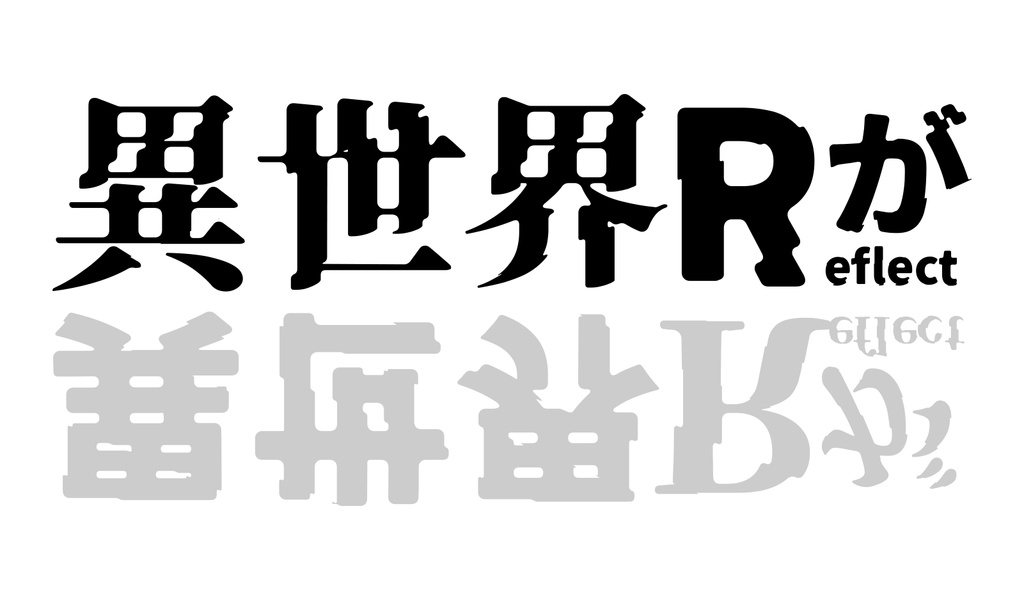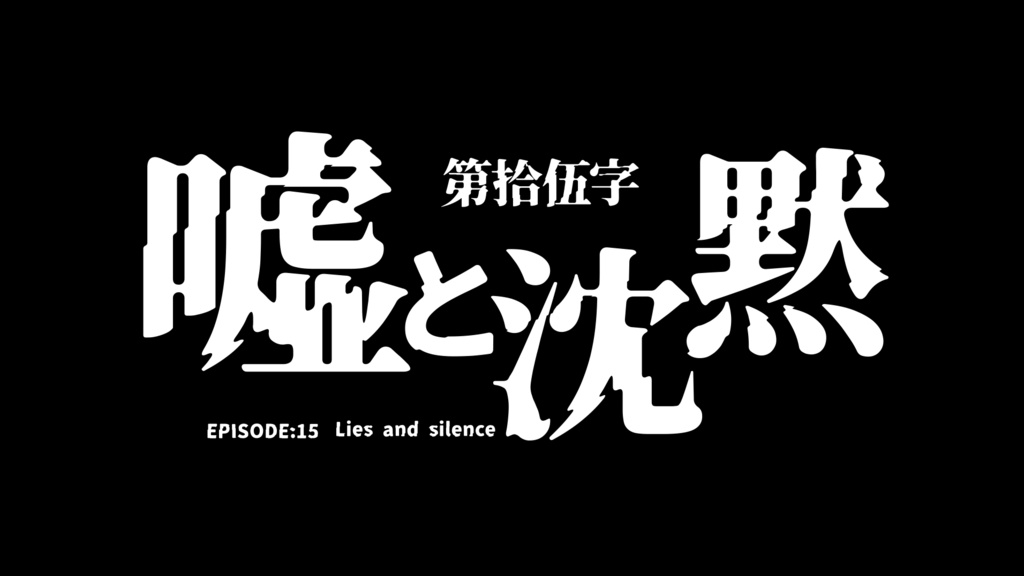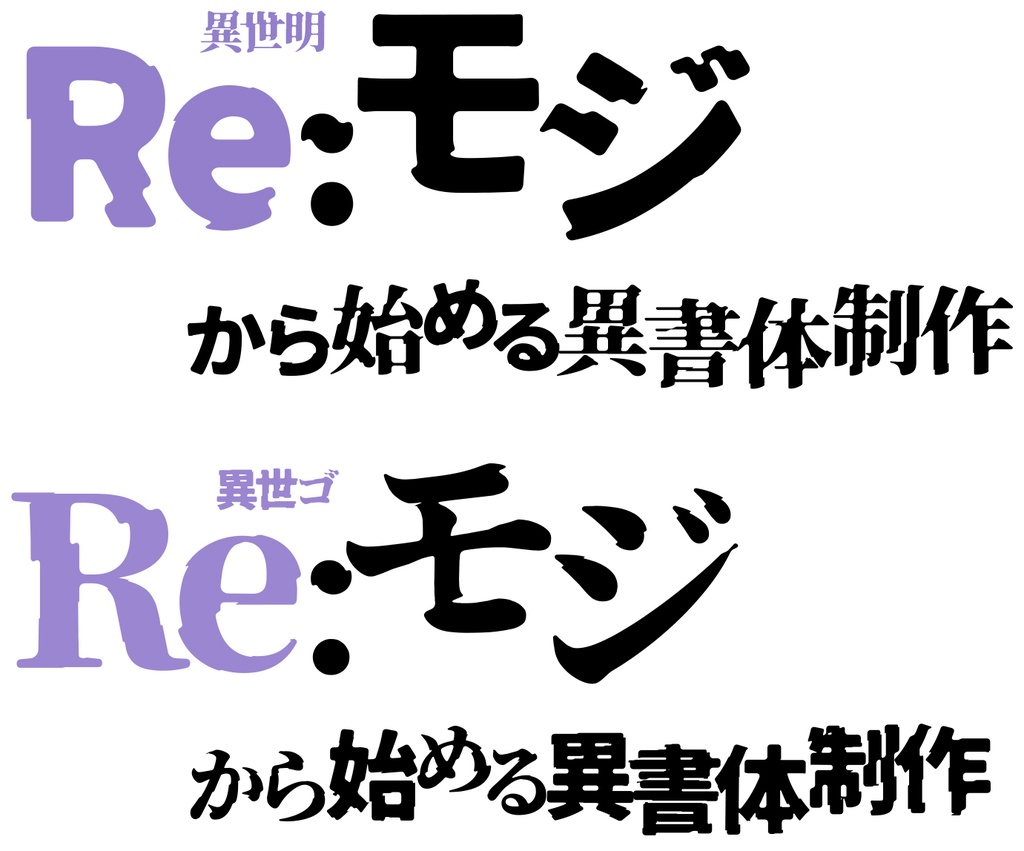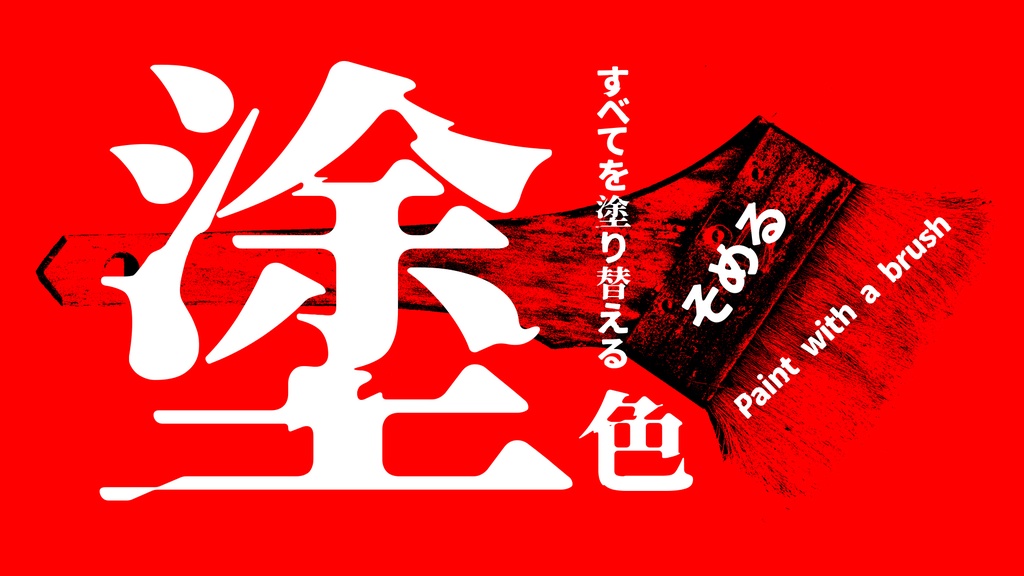
異世明・異世ゴ(フリーフォント)
異世明・異世ゴの2つのフォントのセットです。 「異世明」は漢字が明朝体で、その他の文字がゴシック体のフォントです。逆に「異世ゴ」は漢字がゴシック体で、その他の文字が明朝体のフォントです。 異世界に転移(ワープ)するときに「ぐにゃ」っと世界が歪むような崩れた感じのデザインになっています。かなり特殊な見出し・ロゴ向けのフォントに属すると思います。 ■フリーフォント使用に当たって フォントをインストールして頂くとパソコンのワープロ、グラフィックソフトなどのアプリケーションを使って自由にデザイン、印刷することができます。個人利用・商用利用にかかわらず、無償で使用することができます。当フォントはSIL Open Font License 1.1のオープンソースライセンスに準じます。 ■異世明、異世ゴの概要 異世明、異世ゴは「源ノ明朝」「源ノ角ゴシック」のフォントを改変して制作した派生フォントです。 制作に関わる全ての方に深くお礼申し上げます。 当フォントはFontlabStudio、武蔵システム(http://opentype.jp/)OTEditで作成しました※フリーフォントのインストール・ソフトでの使用についてのサポート・お問い合せは受け付けません。 ⚠️このフォントは自由に動画に使えるフォントです。ご利用の際は次のクレジットを入れていただけると、ものすごーく喜びます! –––––––––––––––––––––––––––––– フォント:異世明または異世ゴ フリーダウンロード:https://booth.pm/ja/items/2291468 –––––––––––––––––––––––––––––– お好きなSNSをフォローしてください。 Instagram ▶ https://www.instagram.com/flopdesign.font X ▶ https://twitter.com/flopdesign Threads ▶ https://www.threads.net/@flopdesign.font